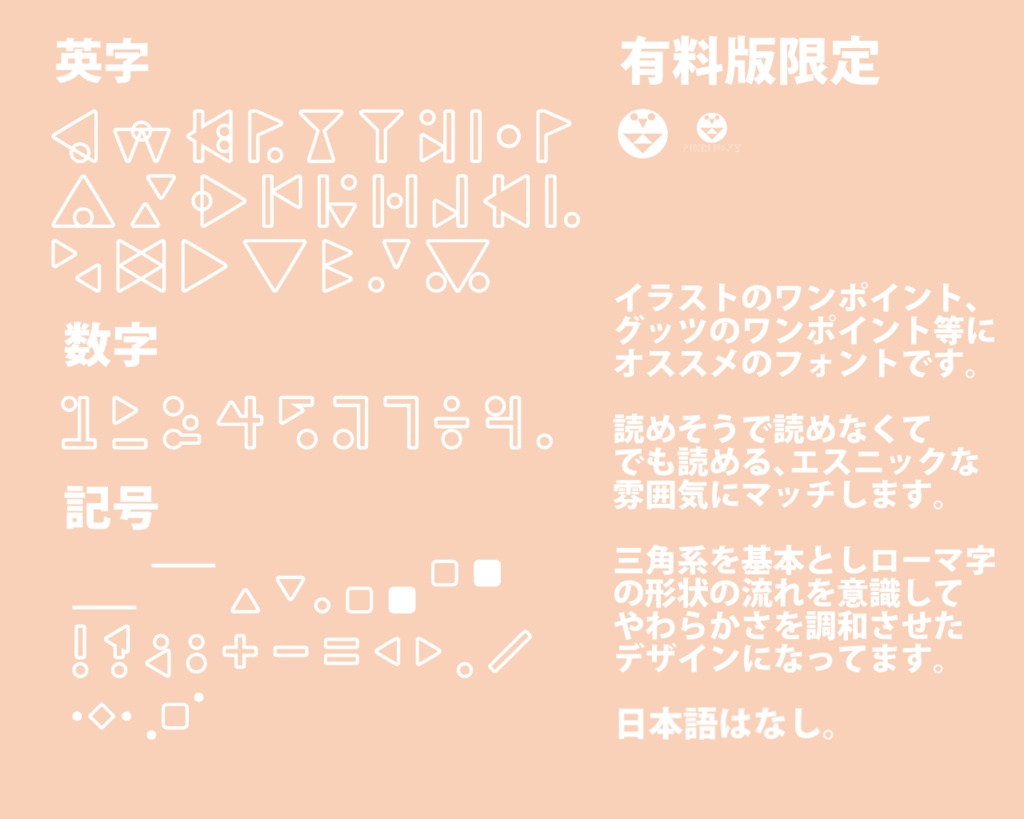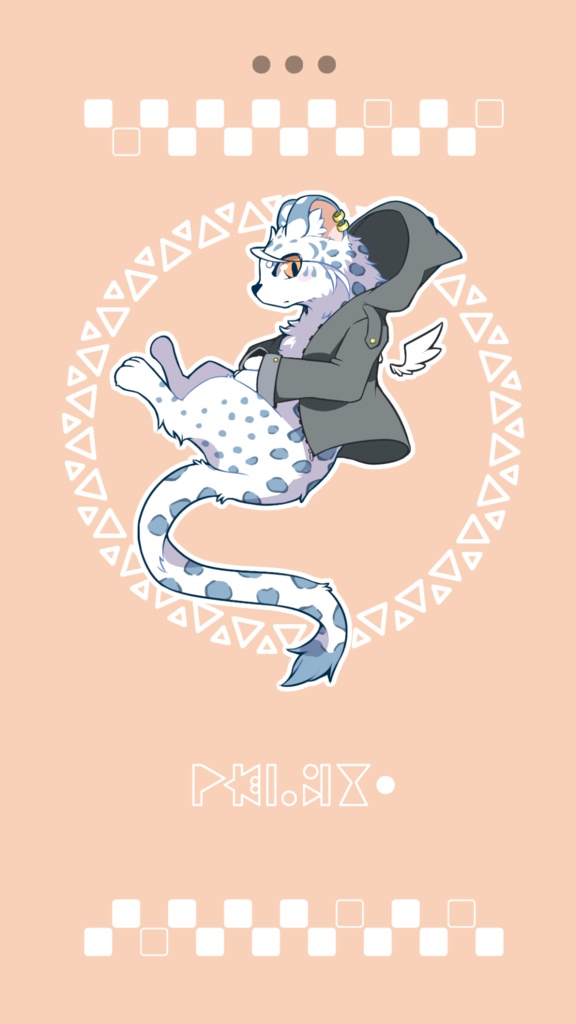
ぴえりフォント
イラストに添えるのに適した、エスニック調の”ぴえりフォント”です。 3枚目の画像は使用例。 フリー版、有料版の2種類があります。ファイル形式はTTFです。 全ての環境での正常な動作の保証はいたしませんのでご了承ください。 作者は著作権の放棄をしていません。なにか損害等があった場合に関しては作者は責任を負いません。また、当フォントはダウンロードした時点より規約に合意したものとみなします。 また、文字の追加等なにかご要望があれば気軽にメッセージを送ってください。 気軽にクレジットしていただけると嬉しいです。 2020/07/01 1.0ver の頒布になってます。 2020/11/20 1.2Ver 「6」の修正 有料版を既にお持ちでバージョンの更新をしたい方はツイッターのほうにDMおねがいしますね! また、フリー版、有料版共に以下項目は禁則事項となります。 ○当フォントの再配布、販売 ○改変や改造等、作者の意図しない使用方法や作者の良くないと思う行為 ○TVや新聞等メディア媒体での利用 ○R-18を基調とした商業製品での利用